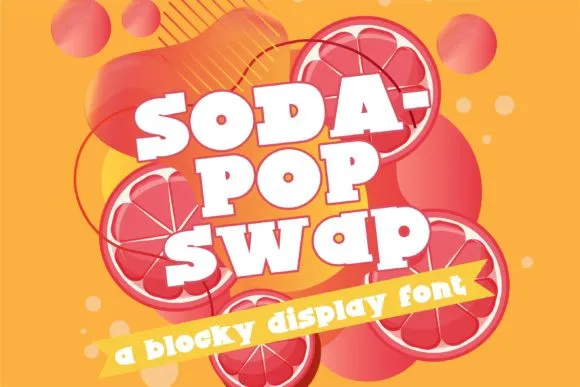
Sodapop Swap Display Font
A ‘Sodapop Swap Display Font’ é uma elegante escolha para criar visuais atraentes e inovadores, especialmente quando se trata de títulos e identidades visuais. Seu design único, com sua tipografia serif que lembra blocos redondos e um pouco esticados, torna-a ideal para uso em diferentes ambientes gráficos. Seja no formato de uma exibição de título poderosa, em uma grande fita informativa na entrada da loja ou até mesmo na criação de um poster chamativo – a ‘Sodapop Swap Display Font’ atende perfeitamente a essas necessidades. Com seu design moderno e clássico ao mesmo tempo, esta fonte é uma ótima adição para designers que desejam dar um toque único em suas criações visuais.